Englische Linie
Typografische Bezeichnung für eine Linienform, die sich dadurch auszeichnet, dass sie an den Enden fein ist und zur Mitte hin dicker wird. Es existieren unterschiedliche Formen, die auch Stilepochen, beispielsweise dem »Jugendstil« oder dem »Art déco«, zugeordnet werden können.
Ursprünglich wurden mit klaren oder verzierten Linien Textpassagen in Büchern und Zeitungen gegliedert bzw. von einander getrennt. Im Zuge der Industrialisierung – in England ab der zweiten Hälfte des 18. Jahrhunderts – und der dadurch aufkommenden »Reklame«, also das werbliche Anpreisen eines Produkts in Form eines Inserats in einer Zeitung oder auf einem Plakat, wurden besonders gestaltete ein-, zwei- oder mehrstückige Linien in England ab Anfang des 19. Jahrhunderts auch zur Gestaltung von Akzidenzdrucksachen verwendet. Mit der Industrialisierung verbreitete sich diese spezielle englische Linienform dann auch in Kontinentaleuropa.
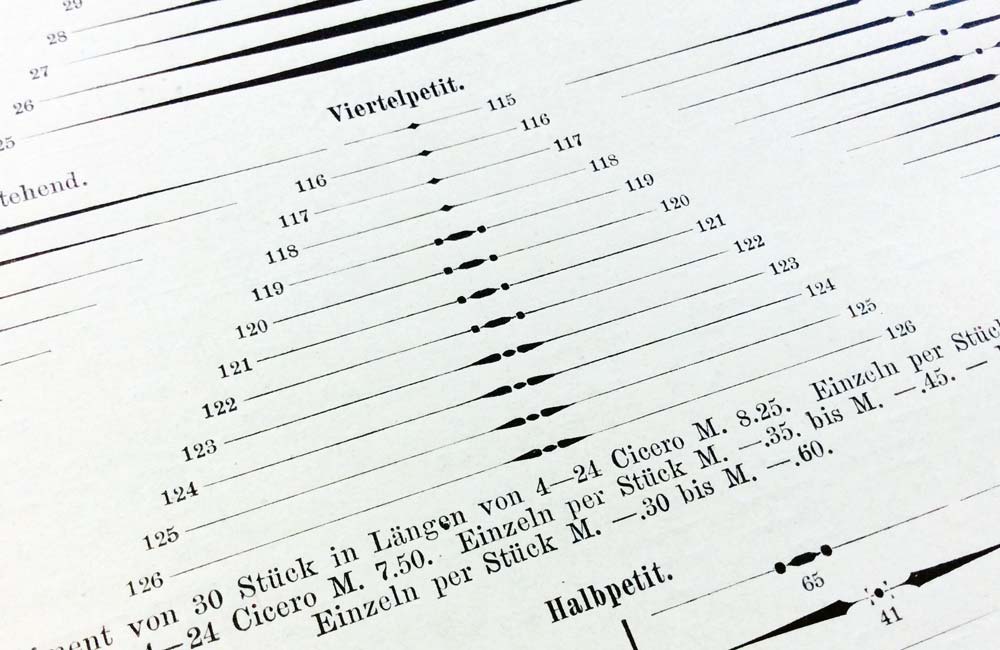
Englische Linien gehörten im materiellen Schriftsatz (z.B. Bleisatz) zu den Alineas bzw. zum »Zierrat«. Sie wurden in der Regel aus Kupferlegierungen (z.B. Messing) hergestellt. Aufwendig gestaltete Linien, beispielsweise moussierte oder gravierte Messingschlusslinien wurden meist bei den Akzidenzschriften aufbewahrt.
Englische Linien gab es in unterschiedlichen Größen und Längen, u.a. in Viertelpetit oder Halbpetit oder u.a. von vier bis vierundzwanzig Cicero. Sie wurden einzeln per Stück oder im Sortiment verkauft, große Chargen auch nach Gewicht.
Englische Linien sind heute auch als Computer Font in OpenType-Formaten erhältlich, beispielsweise der Font »Woodtype Ornaments One« und »Woodtype Ornaments Two« von Barbara Lind und Joy Redick (1990) bei Linotype®.